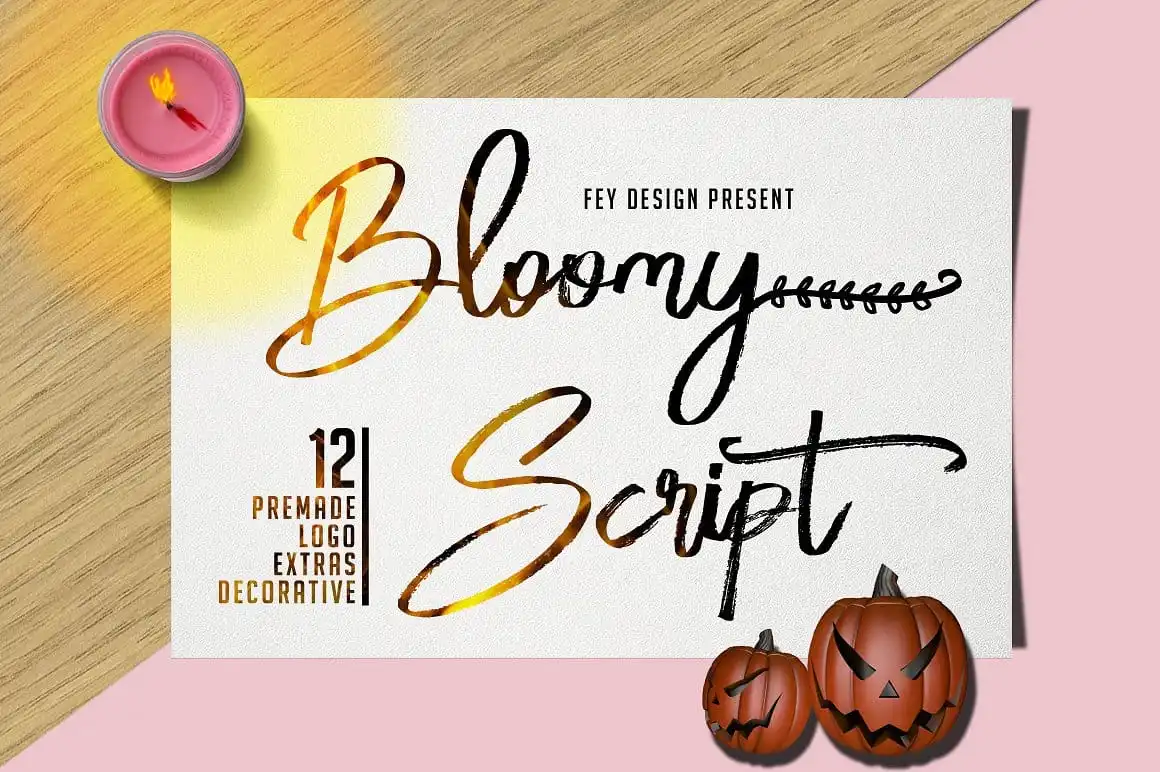
Bloomy Script Font – Download Grátis
Descubra a beleza minimalista e sofisticada desta nova fonte de script com a Bloomy Font de Hamilton. Introduzida pela FeyType Std., esta fonte é uma excelente escolha para projetos de design. A Bloomy Script é um Dry Brush Script que incorpora elementos de escritura à mão moderna, desenhos decorativos e 12 logomarcas prontas para uso. Perfeita para o design, gráficos elementais, eventos, camisetas, logos, selos, adesivos e até mesmo trabalhos incríveis. Seja você designer de moda ou arte digital, a Bloomy Font é certamente um complemento que pode enriquecer seus projetos em vários cenários. Aproveite essa fonte única para dar uma nova dimensão à sua identidade visual.